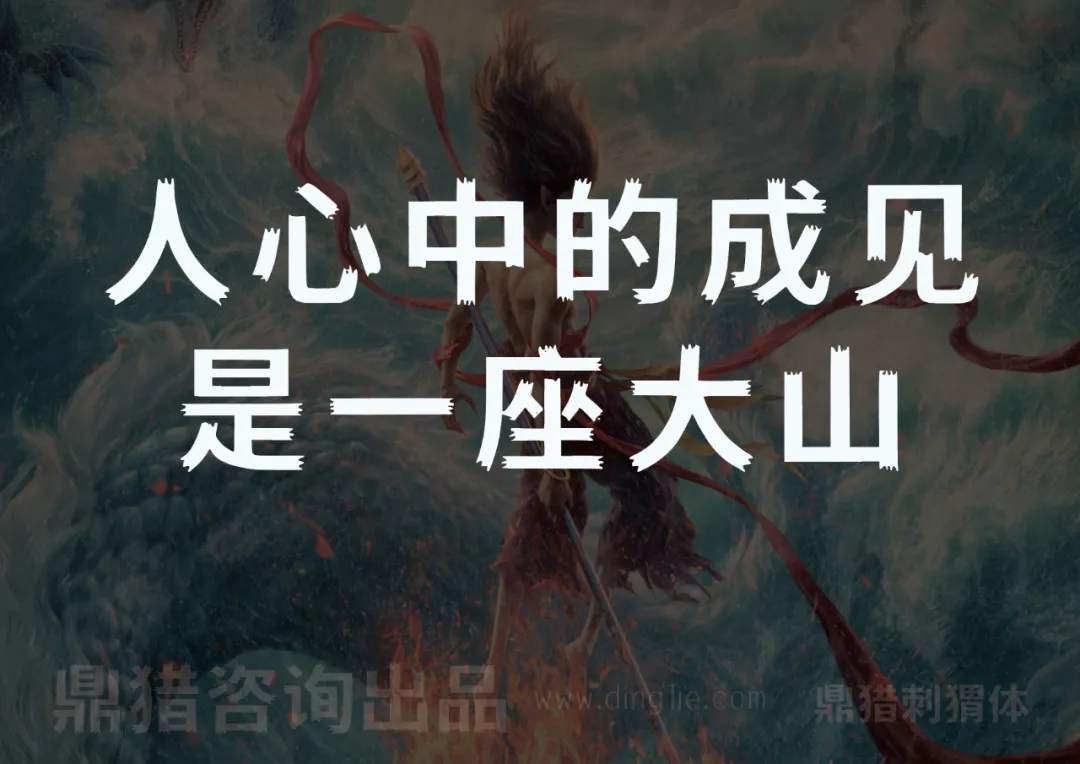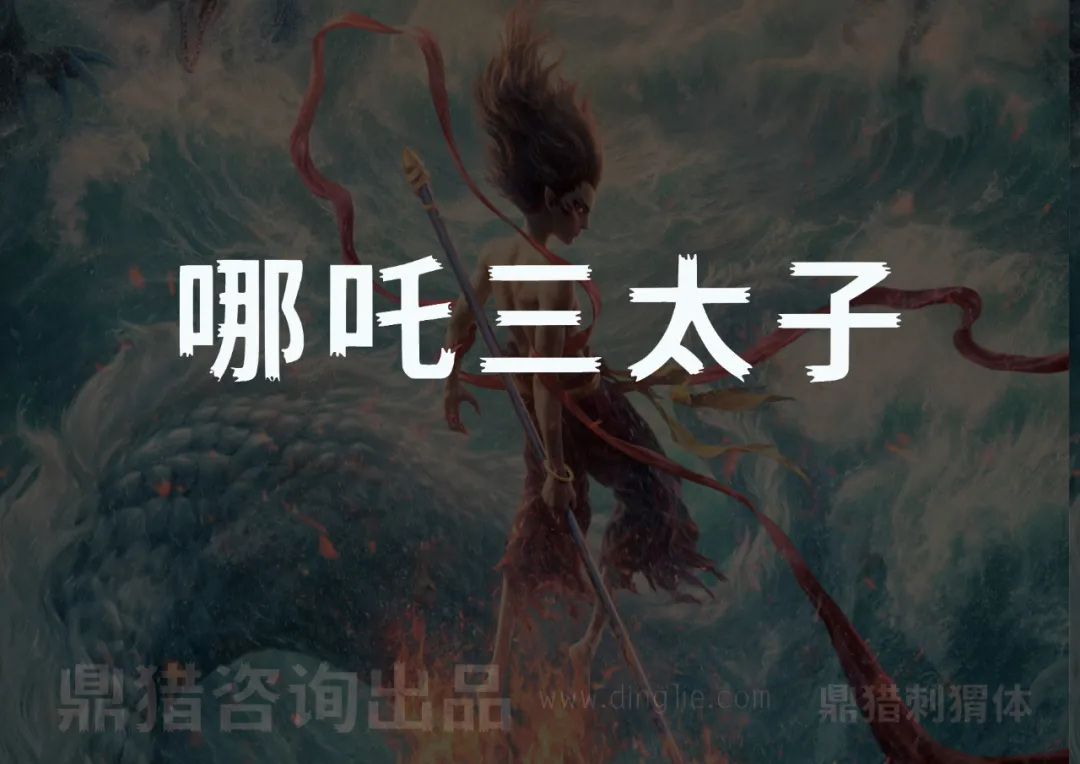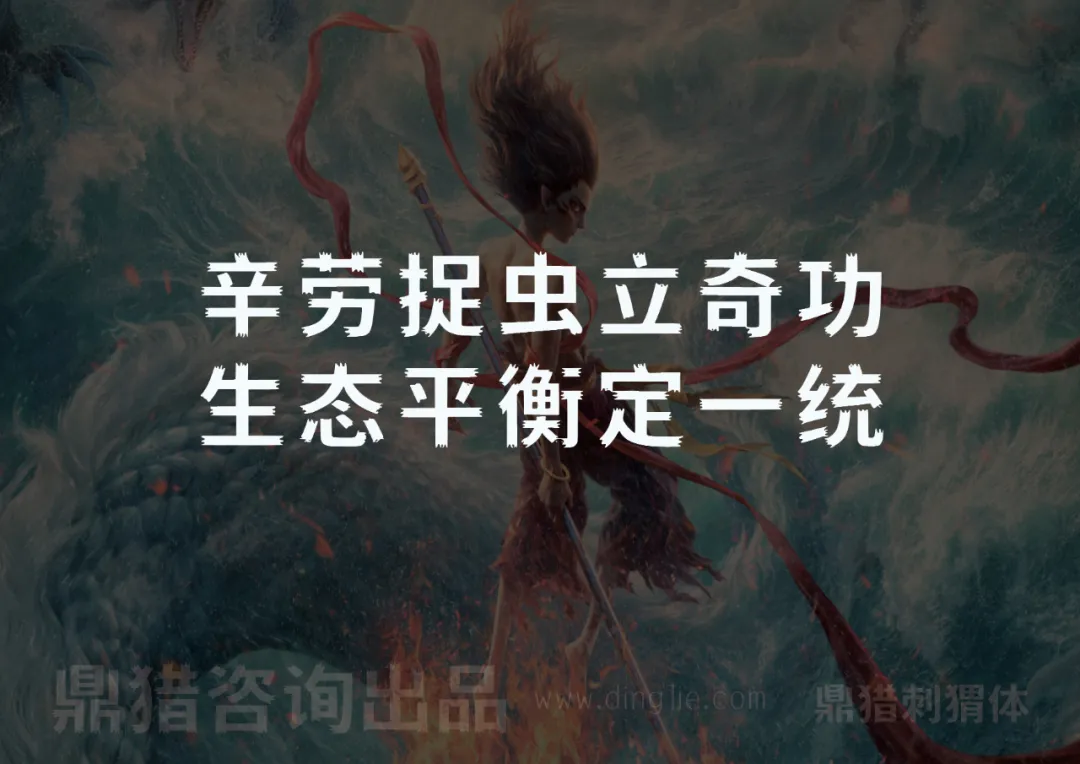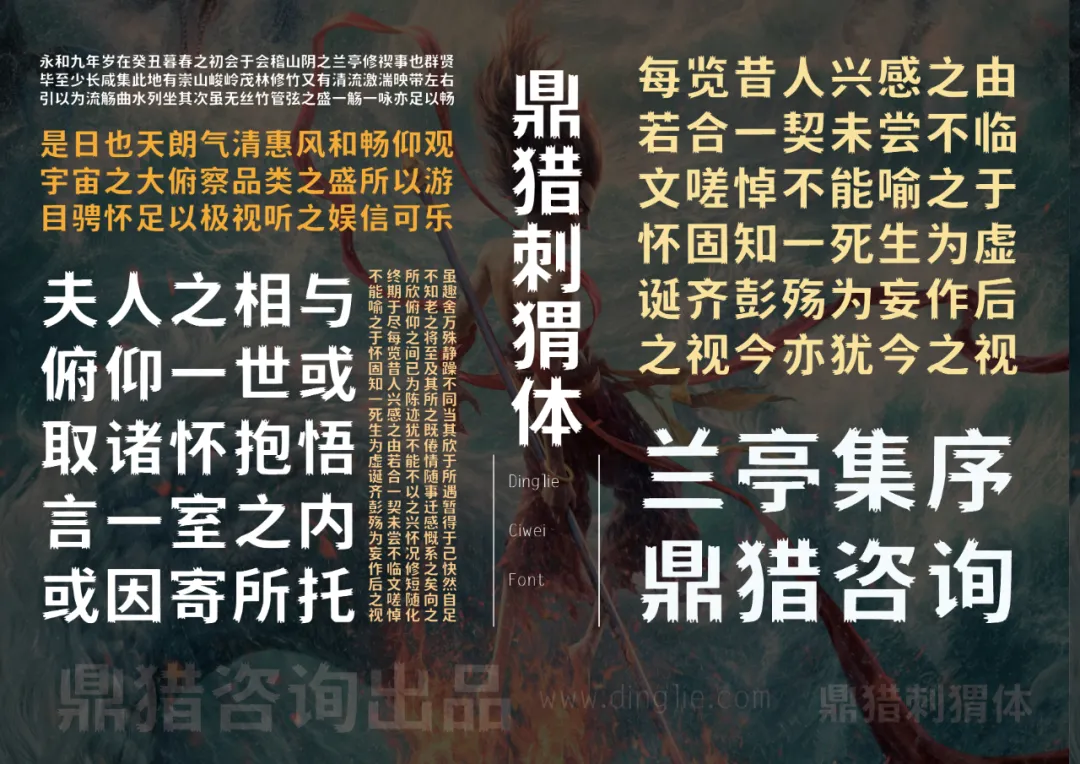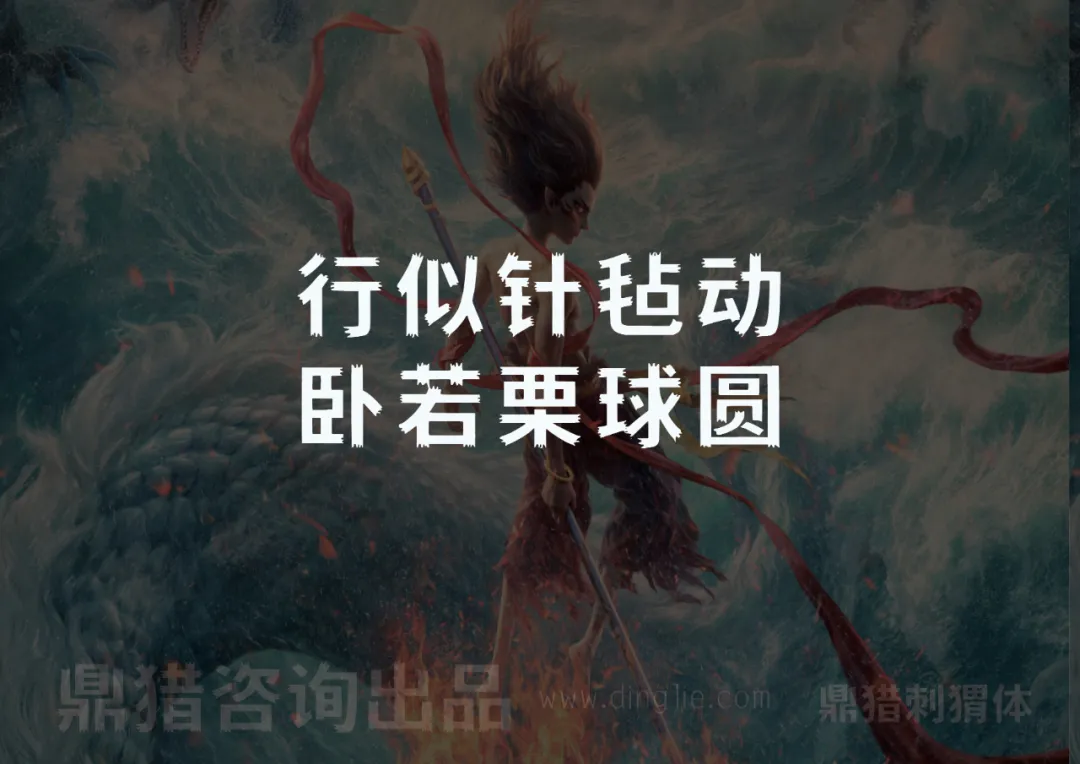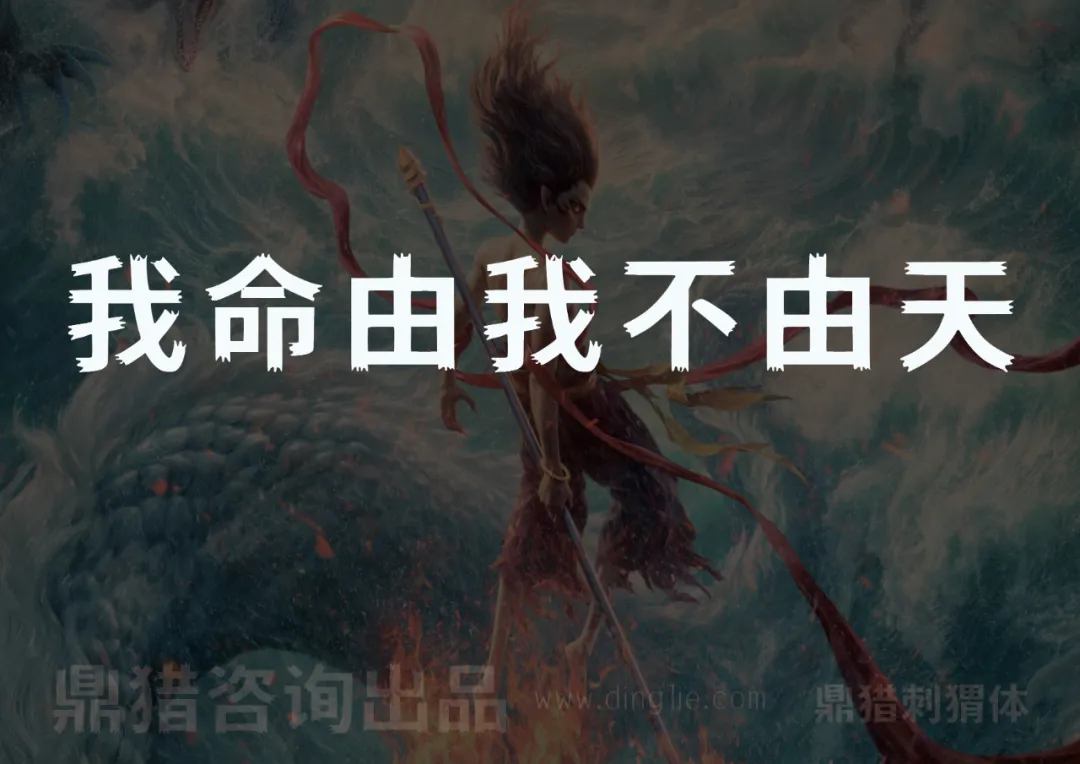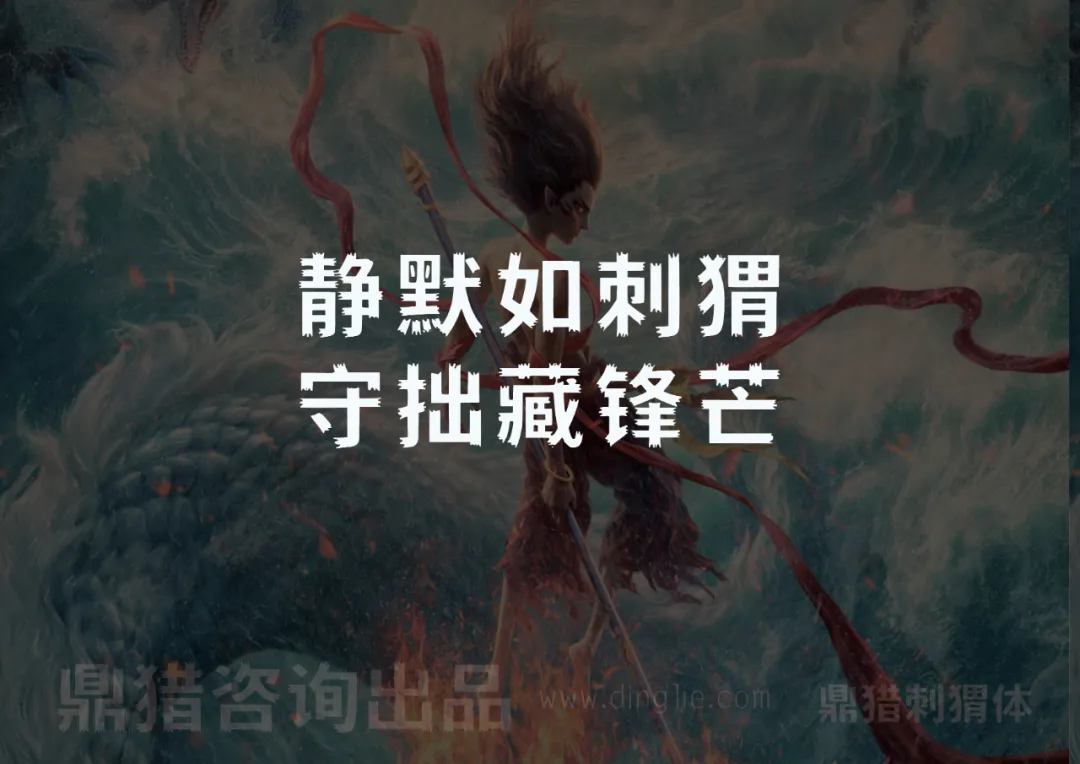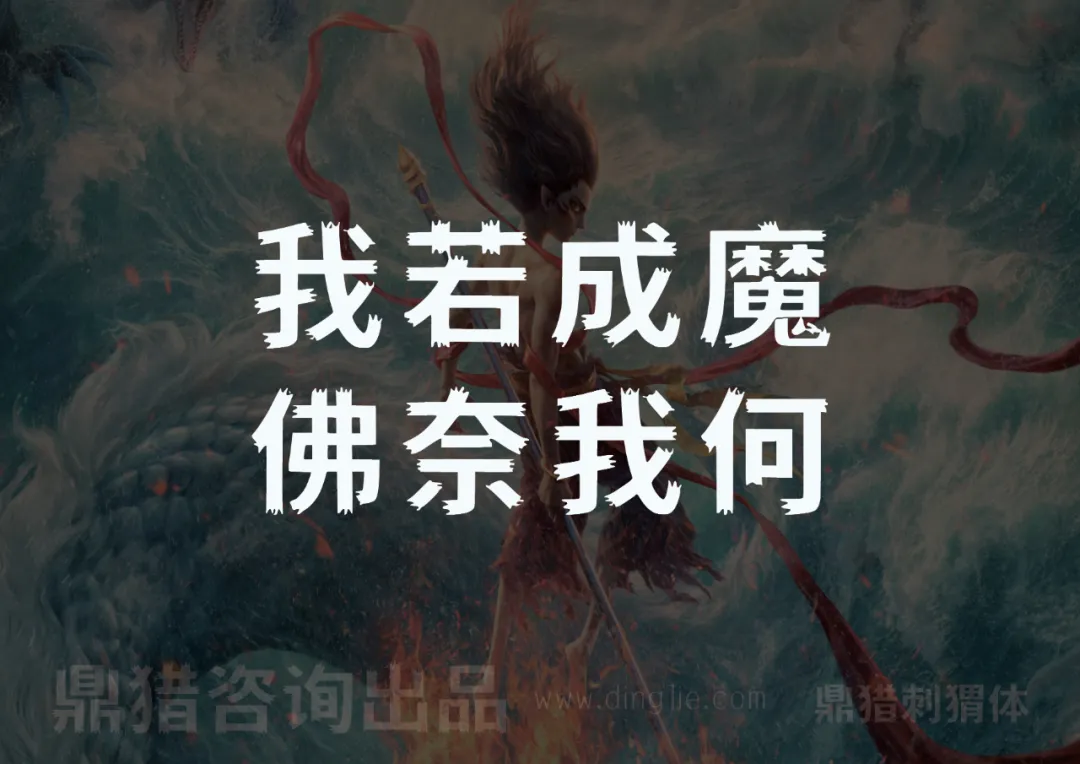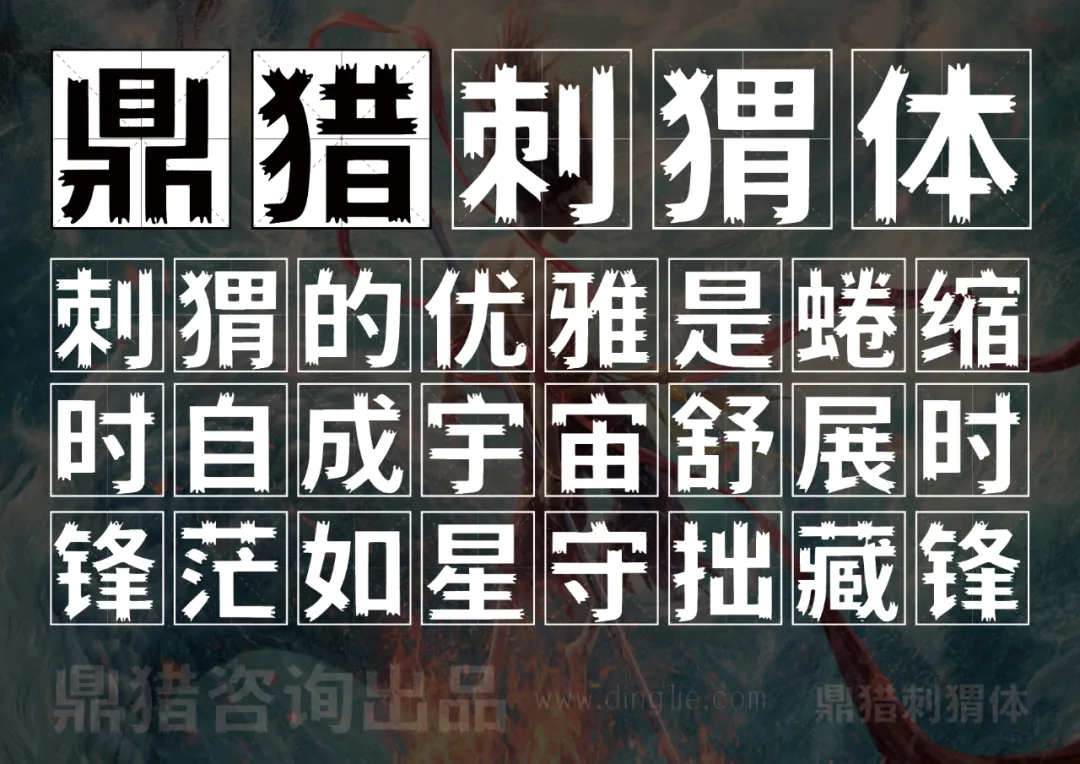
鼎猎刺猬体,是一款以黑体为蓝本衍化的创意字体,整体有撕裂的锯齿状边缘,有稳健和善良的内在,却有着棱角和锋芒,像是刺猬,有锋芒而不失柔软的善良和坚强的意志。很像仍在火热上映《哪吒2》的魔丸哪吒。鼎猎刺猬体适合美食餐饮、展会展览、企业文化,以及报刊封面、餐饮茶饮、美妆护肤等各个行业。踏入2025年,鼎猎将持续推出更多字体。
鼎猎刺猬体:刺猬的优雅是蜷缩时自成宇宙舒展时锋茫如星守拙藏锋,鼎猎咨询出品 www.dinglie.com-刊刻Kntuk
考虑到字体应尽可能满足各类型的姓和名,
鼎猎刺猬体以简体中文汉字编码国家标准(GB2312编码)为标准,
共计设计了多达7415个字符,其中汉字6769个。
可以满足绝大部分印刷设计等要求。
鼎猎刺猬体字体样张,以《兰亭集序》文本排版,展示兰亭集序、鼎猎咨询及鼎猎咨询出品等字样-刊刻Kntuk
哪吒三太子,鼎猎刺猬体,鼎猎咨询出品-刊刻Kntuk
哪吒手持长枪身缠红绫,配文我命由我不由天,底部有鼎猎咨询出品及网址-刊刻Kntuk
以哪吒风格插画为背景,主文字“我若成魔 佛奈我何”,底部标注“鼎猎咨询出品”及网址-刊刻Kntuk
人心中的成见是一座大山-刊刻Kntuk
鼎猎刺猬体字体样张,展示文案静默如刺猬守拙藏锋芒,鼎猎咨询出品-刊刻Kntuk
辛劳捉虫立奇功 生态平衡定一统 鼎猎咨询出品-刊刻Kntuk
鼎猎刺猬体字体展示,背景为神话人物插画,文字内容为行似针毡动卧若栗球圆-刊刻Kntuk